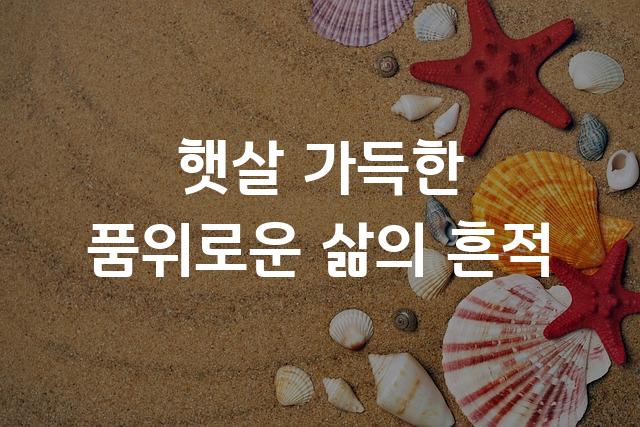
광양감동체는 광양시청과 투게더그룹이 협력하여 제작한 기본 고딕 스타일의 폰트입니다. 현대적 감각과 전통적인 우아함이 조화를 이루며, 사용자에게 깊은 인상을 남깁니다.
기본 고딕, 감성적인, 부드러움 계열의 생김새를 가지고 있으며
간판, 카페 메뉴 등에서 자주 활용되며, 효과적인 메시지 전달에 적합합니다.
이 폰트는 음식/식음료, 이벤트/웨딩 분야에 잘 어울리며,
친근한, 신뢰감 느낌을 담고 있는 것이 특징입니다.
이 폰트와 유사한 폰트로는 나눔고딕, 말랑말랑체, 서울한강체 등이 있어요. 함께 비교해 보시면 좋습니다!